[동네책방의 매력] 1. 뷔페 같은 동네책방, 땡스북스
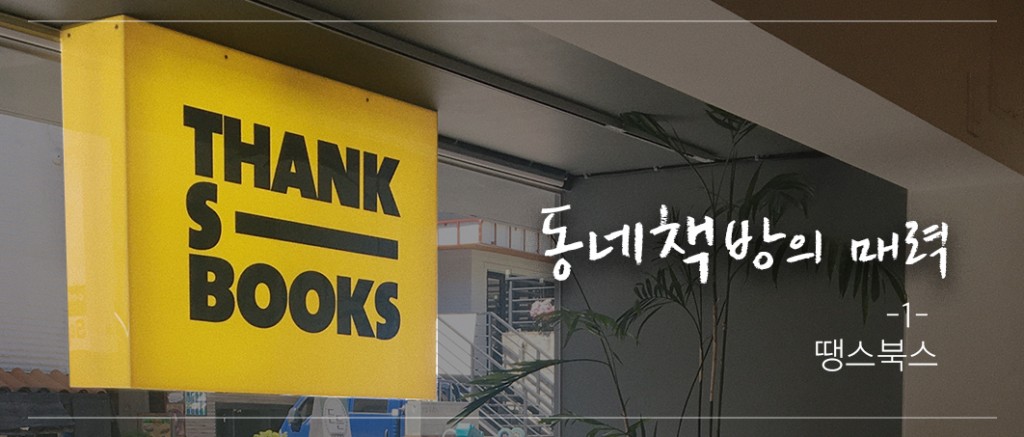
“취향껏 책을 맛볼 수 있는 뷔페 같은 동네책방”
‘동네책방의 매력’ 기획연재의 첫 번째 주인공은 바로 ‘땡스북스’이다. 책을 좋아하는 사람들이라면 홍대 앞, 동네책방의 랜드마크라고 할 수 있는 땡스북스를 쉽게 지나칠 수 없을 것이다. 7년 동안 한 자리를 지켜왔던 책방은 지난 5월, 합정역과 조금 더 가까운 곳으로 자리를 옮겼다. 전보다 소박한 모습이지만, 모든 공간이 온전히 책으로 채워져서일까? 어쩐지 책에 눈길이 더 많이 간다. 가운데 길게 뻗은 책상은 좀 더 편하게 책을 살펴볼 수 있게 해주는 새로운 땡스북스의 자랑거리다. 북큐레이터 손정승 점장(이하 정승)과 염한별 매니저(이하 한별)와 더위를 잠시 잊게 해준 유쾌한 대화를 나눴다.
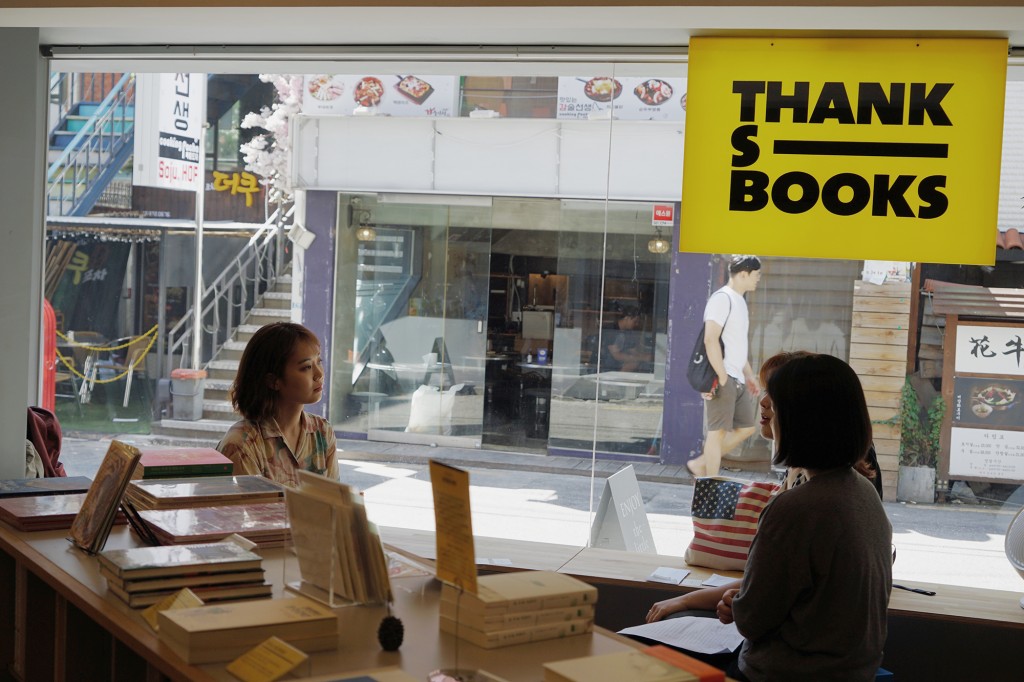
안녕하세요. 두 분은 땡스북스에서 어떻게 일하게 되셨나요?
정승: 땡스북스의 점장 손정승입니다. 올해로 일한 지 3년 차 됐고요. 땡스북스에 들어오는 전반적인 책 선별부터 모든 이벤트를 염한별 매니저와 함께 진행하고 있습니다. 저는 국문학을 전공했고 원래는 출판사에 취직하려 했어요. 좋은 기회로 일을 시작했는데 생각보다 되게 재미있더라고요. 책으로 할 수 있는 일이라는 게 편집, 디자인, 홍보 이런 것만 있는 줄 알았는데 여기서는 책으로 전시도 하고, 금주의 책도 소개하는 등 정말 다양한 것을 하는구나 싶었죠. 저도 제가 서점에서 일하게 될 줄은 몰랐어요.
한별: 안녕하세요. 염한별입니다. 일한 기간은 1년 반 정도 되었고요. 저는 개인적으로 독립서점을 차리고 싶었어요. 운이 좋게 땡스북스 공고를 보고 2016년부터 아르바이트로 일하다 보니, 당시 점장님이 퇴사하시면서 자리가 생겨 시작하게 되었습니다.
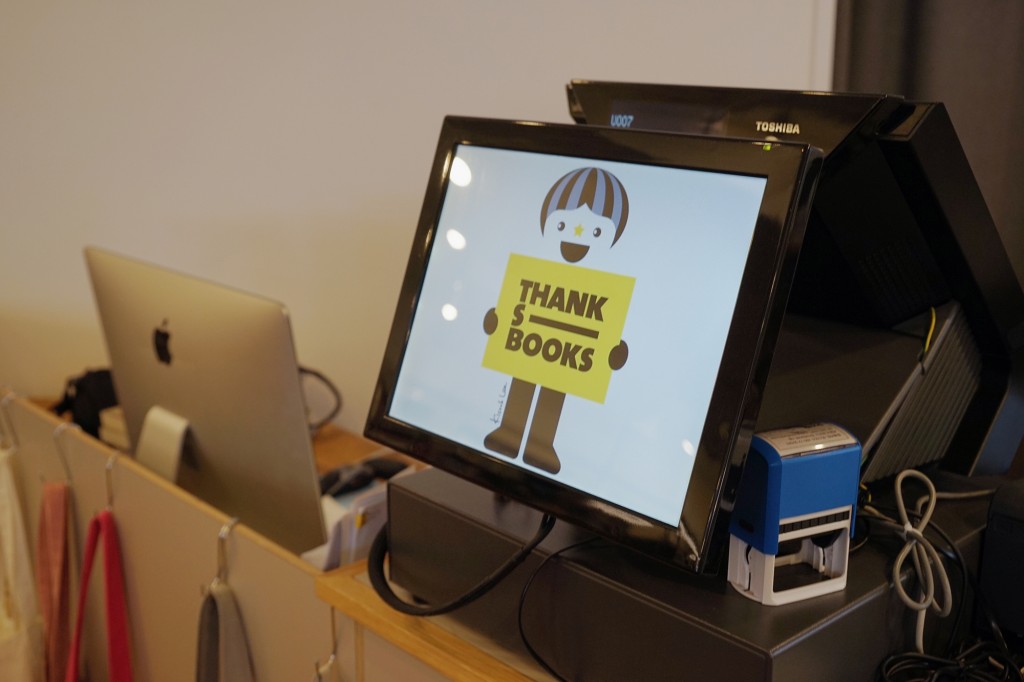
두 분 다 기회를 잡으셨네요. (웃음) 보통 출근하셔서 퇴근하기까지의 하루는 어떻게 보내시나요? 12시에 문을 열죠?
정승: 네. 12시 조금 전에 출근해서 오픈준비를 해요. 청소하고 전날 쌓인 먼지를 털어내고 그렇게 30분 정도 준비를 해요. 그다음에는 메일을 확인합니다. 오후에는 책이 들어오는 시간이라 서가에 진열하고, SNS에 신간을 찍어서 올려요. 아 물론, 손님응대는 계속하고요. 저녁때부터는 출판사 직원분들이 퇴근하시니까 조금은 더 저희만의 시간이죠. 그 시간에 회의를 많이 하는 것 같아요.
한별: 보통 출판사 근무하시는 분들이 오후 여섯 시까지 근무를 하시니까 그때까지는 입고문의 같은 전화가 많이 오는 편이에요. 동시다발적으로 해야 할 일이 많죠.
멀티플레이어가 되어야 하는 직업이군요. 하나에만 집중하기도 힘들텐데 대단하세요. 혹시 특별히 기억에 남는 손님이 있으신가요?
한별: 주말마다 오시던 단골손님이 제주도로 이사를 하셨어요. 중년 남성분이셨는데 항상 오실 때마다 대여섯 권씩 구매하시는 분이셨거든요. 그런데, 어느 날 서울 온 김에 왔다고 하시면서 책방에 오셔서 책 한 박스를 제주도로 배송하셨어요. 제주에도 책방이 많은데, 굳이 택배비를 들여가지고 그렇게 해주신 게 놀랐어요. 정말 감사하죠. 말 그대로 의리가 아니었을까.
그 분은 땡스북스라는 공간에서 책을 고르시는게 정말 좋으셨나봐요. 점장님도 에피소드가 있으신가요?
정승: 저는 저번 달에 만난 손님인데요. 재고가 소진되고 샘플만 남은 책이 있었어요. 어떤 분이 그 책을 구매하겠다고 하셔서 책 상태가 좋지 않아 판매가 안 될 것 같다고 했는데, 괜찮다고 사겠다고 하시는 거예요. 할인해서 드리면서도 마음이 편치 않아 샘플을 드려서 죄송하다고 그러니까 “아니에요. 이렇게 좋은 책을 둬 주셔서 고맙습니다”라고 하셨어요. 그때 마음이 아주 따뜻했어요. 하루에도 몇십 종씩 책이 쏟아지는데, 매번 고민해서 책을 고르는 마음을 알아주셨다고 해야 할까요.
땡스북스의 책은 어떤 기준으로 큐레이션 되는지 궁금합니다.
정승: 책의 디자인과 콘텐츠가 다 중요하고 그런 책들을 위주로 고르지만 조금 더 사적인 것을 더하자면 ‘저희가 읽고 싶은 책’이에요. 물론 판단이 틀릴 때도 있지만, 아무래도 책 가까이에서 일하는 저희가 제일 먼저 설득이 되어야 남도 설득될 수 있다는 생각을 해요.
한별: 그동안 꾸준히 쌓아왔던 데이터가 있잖아요. 땡스북스에 찾아오시는 분들이 어떤 것을 좋아하는지에 대한 감이 있는 거죠. 느낌으로 판단해요. 판매량 같은 데이터를 살펴보기도 하고, 판매가 잘된 책과 비슷한 책, 저희가 재미있을 것 같은 책들을 찾아서 배치하는 편이에요.
직관적으로 땡스북스에 어울리는 책을 알아보시는 거네요. 그런데, 서가에 카테고리가 없어요. 주제별로 나눠져있는거죠?
한별: 네. 매대에는 땡스 초이스 코너, 신간 테이블, 전시에서 나온 책들 등이 있고 서가는 라이프스타일, 실용서, 문학, 에세이, 영화, 음악 등 주제별로 책이 나뉘어 있어요.
처음에는 저희도 카테고리를 달아야 하나 싶었는데, 어떤 손님이 오셔서 “카테고리가 없어서 좀 더 천천히 살펴보게 된다”라고 하셔서 없는 것도 그것만의 매력이 있지 않을까 싶어서 안하기로 했어요. (웃음) 물어보시는 분들이 있으면 안내해드리고 있어요.
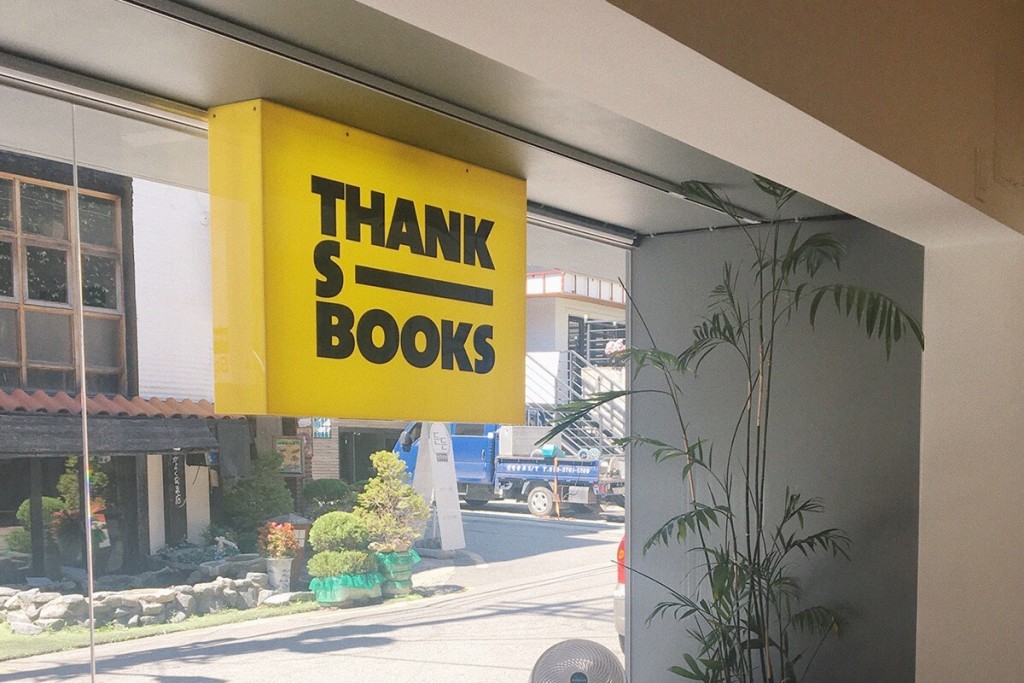
다음은 항상 궁금했던 질문입니다. 땡스북스 간판의 폰트는 무엇인지, 디자인에는 어떤 의미가 담겨있는지 알려주세요.
한별: 로고는 이기섭 대표님께서 만드셨는데, 우선 폰트는 ‘TheSans’ 이고요. 당시 헬베티카를 사용하실 고민하셨는데, 최종 선택은 이 폰트였다고 해요. 땡스북스와 잘 어울리고, 제일 끌려서 이 폰트로 쓰셨다고 합니다.
정승: 그리고 로고 가운데 긴 직선은 책등을 뜻한다고 해요. 땡스북스를 영어로 쓸 때, 글자수를 보면 BOOKS에 비해 THANKS에서 ‘S가’ 한 자 더 있잖아요. 지금 위치에서 위로 올리면 비율이 안 맞아서 가운데로 내리셨다고 하셨어요.
아, 저 직선이 항상 궁금했는데 책등이었군요!
정승: 네. 책의 가장 단순한 형태를 떠올렸을 때, 책등이라고 생각하셨나 봐요. 그리고 땡스북스가 따뜻한 공간이었으면 하는 마음에서 로고의 색깔을 노란색을 선택하셨다고 해요. 보시면 원색의 노란색이에요. 다양한 색을 담을 수도 있는데, 그냥 노란 바탕에 검은색으로 하신 게 실용적인 측면도 고려하신 거에요. 원색이 아니었다면 이 로고를 사용해서 무언가를 만들 때마다 매번 감리를 가야 하는 거죠. 우리의 간판이고 정체성이니까 로고의 색이 달라지면 안 되니까요. 그런 효율적인 면도 생각하신 것 같아요.
땡스북스를 찾으시는 손님들의 공통적인 특성이 있을까요?
한별: 보통 2,30대 여성이 대다수였는데 이전하고 난 후, 연령대가 다양해진 것 같아요. 여기는 회사사무실이 많으니까 점심시간에 오셔서 책 보고 가시고 그래요.
정승: 본인을 알려고 하는 분들이 많이 오시는 것 같아요. 최소한 알려고 노력하는 사람이요. 실은 일에 치이다 보면 자신을 바라보기 힘들잖아요. 최소한 여기 와서 시간을 들여서 책을 본다는 것은 자기 마음에서 무엇을 원하는지 보려고 하는 거죠.
책을 통해 나름의 해답을 찾고 싶어하시는 분들이겠군요. 그럼 이쪽으로 오시면서 또 변화한 점이 있을까요?
정승: 7년이라는 시간 동안 한 곳에 있었다는 게 참 대단한데, 한편으로는 저희도 바꾸고 싶다는 생각도 들었거든요. 이전 장소는 너무 크니까 아무리 바꿔도 티가 잘 안 나기도 했고, 저희가 초기 멤버가 아니라서 기존의 것을 유지하는 데 급급했어요. 새롭게 시도해보기가 힘들었죠. 여기로 오면서 책에 좀 더 집중하자는 컨셉으로 카페도 과감하게 없앴어요.
땡스북스를 음식에 비유한다면요?
정승: 음식은 아니지만, 식당 중에서 골라봤어요. 바로, ‘뷔페’에요. 뷔페도 기성 음식을 쭉 놓고 먹고 싶은 대로 먹으라고 하는 거잖아요. 비슷하다고 생각했던 게 지금 저희가 독립출판물의 경우, 초기거래처 몇 곳 빼고는 안 받거든요. 기성 출판사 중에서 골라서 들어오는 것인데, 이렇게 책을 진열해 놓으면 손님들이 읽고 싶거나 관심 있는 것을 보신단 말이에요. 뷔페에 가면, 하나씩 맛본 다음에 맛있는 음식 하나만 공략하는 것처럼 몰랐던 책도 들춰보고 마음에 든 순간, 그쪽 분야에 더 관심을 끌게 되는 거죠. 음식으로 치면 어떤 메뉴를 더 정확히 알게 되는 거예요. 취향껏 먹어도 아무도 뭐라고 안 하는 것처럼, 취향껏 책을 보셔도 되는 거죠.
정말 좋은 비유네요. 땡스북스는 뷔페다! 그럼 땡스북스가 홍대에서 긴 시간 동안 사랑받을 수 있었던 이유는 무엇일까요?
한별: 오랫동안 같은 자리에 있던 것이 큰 요인이라고 생각해요. 아시다시피 홍대 앞 가게들은 문닫고 이전하고 그런 곳이 많으니까요. 오랜 시간 기억해주시고 찾아주신 데는 위치적인 요인도 있던 것 같아요.
정승: 초기에 자리 잡을 수 있었던 이유는 타이밍이 좋았던 것 같아요. 2011년에 시작할 당시만 해도 있던 서점들도 문을 닫았고, 홍대 9번 출구 앞에 북스 리브로밖에 없었어요. 다행히 초창기에 젊은 감각으로 사람들의 마음을 잘 잡았던 것 같아요. 그 이후에는 지속하기 위한 노력을 했어요. 공간을 그대로 가꾸기 위해서 저는 그렇게 매일 쓸고 닦고 정리해야 하는지 몰랐어요. 변화도 중요하지만, 유지하기 위한 노력도 중요하다는 것을 알아주신 것 같아요.
이 자리도 오래 지켜주시면 좋겠어요. 마지막으로, 두 분의 ‘인생 책’을 소개해주실 수 있을까요?
한별: 최고의 책은 아니지만, 특별한 경험을 했던 책이 있어요. 할레드 호세아니의 『천 개의 찬란한 태양』이라는 책이에요. 전쟁 이야기를 담은 소설인데요. 제가 과연 읽을 수 있을까 의문스러웠던 두꺼운 책을 다 읽고서 처음으로 엉엉 울었던 기억이 있어요.
정승: 저는 이청준의 『당신들의 천국』이요. 인류애가 소멸할 때마다 한 번씩 읽으면 좋은책이에요. 소록도 이야기인데, 등장인물 중에 한 명이 배신을 해야 될 것 같은데 끝까지 안 하는 사람이 있어요. 이상한 사람들 만날 때 많잖아요. 인간이 뭘까 싶을 때마다 이 책을 보면 그래도 끝까지 배신하지 않았다는 게 위안이 돼요. 또 인간이 이런 생각으로 이런 행동을 할 수 있구나 생각해보게 되는 책이에요.
“저는 대형서점에 잘 못가요. 압도당하는 느낌이 너무 커요. 잘 팔리는 순서대로 쌓여 있고, 거의 제가 찾는 책은 구석에 꽂혀 있죠. 물론, 많은 책을 골라서 집을 수 있다는 장점도 있지만 집 앞에 오래된 동네서점이 있다면 편안한 마음으로 갈 수 있을 것 같아요.”
– 땡스북스 북큐레이터 손정승 점장
“책방에 가서 ‘사장님 오늘 신간 들어왔어요?’ 했을 때, ‘여기 빼놨어’ 이런 식으로 편하게 얘기를 주고받을 수 있는 게 좋아요. 그게 동네책방의 매력이라고 생각합니다.”
– 땡스북스 북큐레이터 염한별 매니저